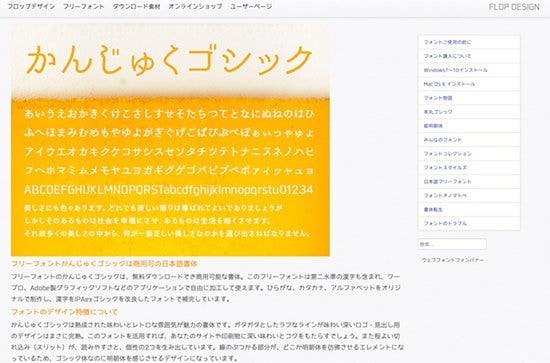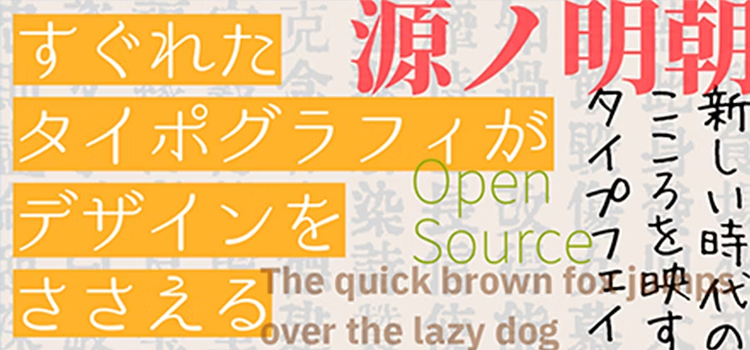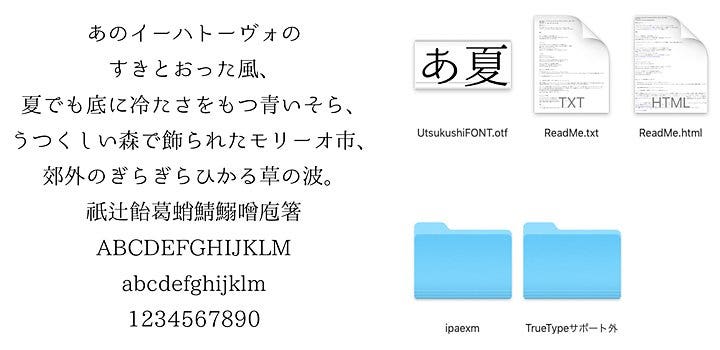
フリーフォントを使いこなしてデザインの幅を広げよう
フォントは文字で情報を伝えるために欠かせないものですが、デザインの表現を豊かにする大切な要素でもあります。さまざまなメーカーから伝統的なフォントやユニークなデザインのフォントが発売されていますが、表情豊なフォントはそれだけではありません。
製作者が無償で提供して自由に使うことのできるフリーフォントにも、多彩なデザインのフォントがラインナップされていて、上手に使いこなせば、より一層デザインの幅を広げることができます。
フリーフォントとは
フォントには有償で販売されているものや、年間のライセンス契約で使用するもののほかに、メーカーや行政法人、個人が無償で提供しているものがあります。
この無償で提供されているものをフリーフォントといいます。
フリーフォントには、漢字とかな、アルファベットが揃っているものから、かなだけのもの、アルファベットだけのものなど、さまざまな種類があり、デザインもオーソドックスな明朝体やゴシック体から、手書き風の文字、毛筆風の文字、機械彫刻を再現した文字、イラスト風の文字といったように、バラエティに富んだものが作られているのも魅力です。
フリーで提供されているフォントは、品質の高い明朝体や、古い活字を復刻したデザイン、手書きの味わいがあるデザインなど、バラエティに富んでいるのが魅力です
オープンソースのフォントとは
フリーフォントの中には、オープンソースとして提供されているフォントがあります。
オープンソースとはもともとコンピューターのプログラムであるソースコードを無償で公開して自由に改良したり再配布を可能にしているもので、オープンソースのフォントであればフォントのデザインを変えたり、自分で改良したフォントを自由に配布することが可能であったりします。
オープンソースとして提供されているものとして、AdobeとGoogleが共同で開発した「源ノ角ゴシック」や「源ノ明朝」、IBMが公開している「IBM Plex」、独立行政法人情報処理推進機構が公開している「IPAexフォント」などがあります。
CCユーザー必携のフォントサービス「Adobe Fonts」
Adobe CCを契約中のユーザーであれば、Adobeと世界中のフォントメーカーやパートナーが提供する15,000以上のフォントが使えるフォントサービス「Adobe Fonts」を逃す手はありません。日本語フォントもフォントメーカー各社の100を超えるフォントファミリーが揃えられています。
フォントライブラリWebサイトでは明朝体やゴシック体、デザイン書体などでフィルターをしたり、フォントメーカーやデザイナーなどで検索して使いたいフォントを選ぶことが可能です。
また、テーマに応じた複数のフォントを簡単にインストールできるフォントパックも用意されていて、カフェメニューや年賀状、名刺など、目的に合わせた複数のフォントを簡単にアクティベートすることができます。
Adobe FontsのフォントライブラリWebサイトでは、フォントの検索やフィルタによる絞り込み、テーマでパックになったフォントの一括アクティべーションなどが可能です